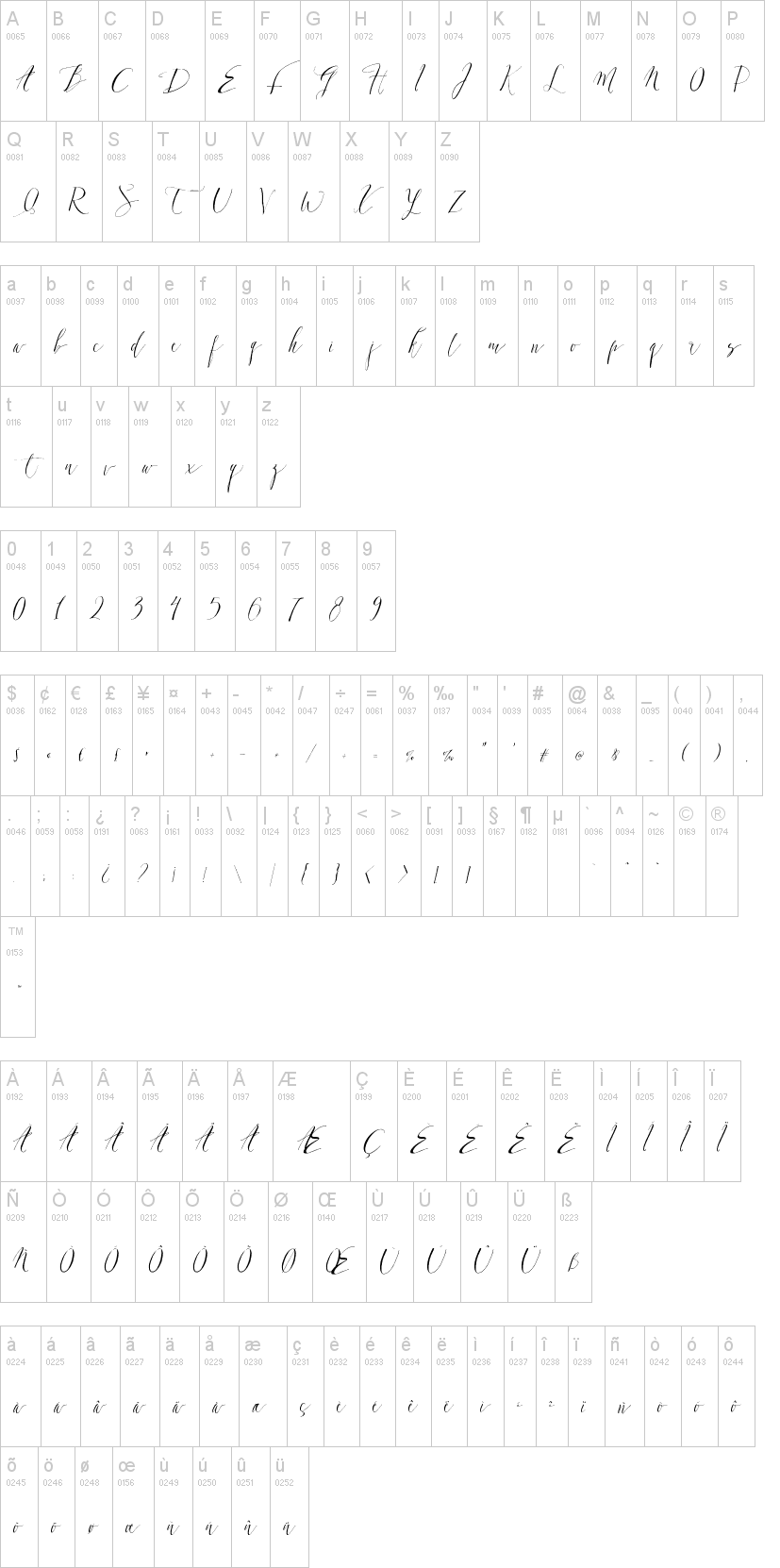
Dearly Script 是一种手写风格的字体,具有流畅、柔和、自然的特点。它的字母和符号都像是由手写字体制作而成,给人一种亲切、温馨的感觉。 该字体适用于多种场合,如婚礼、浪漫的场合、手工艺术品、书信等。它的设计师希望通过这种字体的使用,呈现出更多的人性化和个性化,将字体与人文艺术的融合更加深入。 Dearly Script 是商业字体,可以在许多字体库网站上购买。内容介绍
Dearly Script是一款非常不错的手写艺术字体,具有很好的视觉感,适合于文化类的宣传设计、商业类品牌的广告和产品包装设计以及个性化文字排版等较多场景。